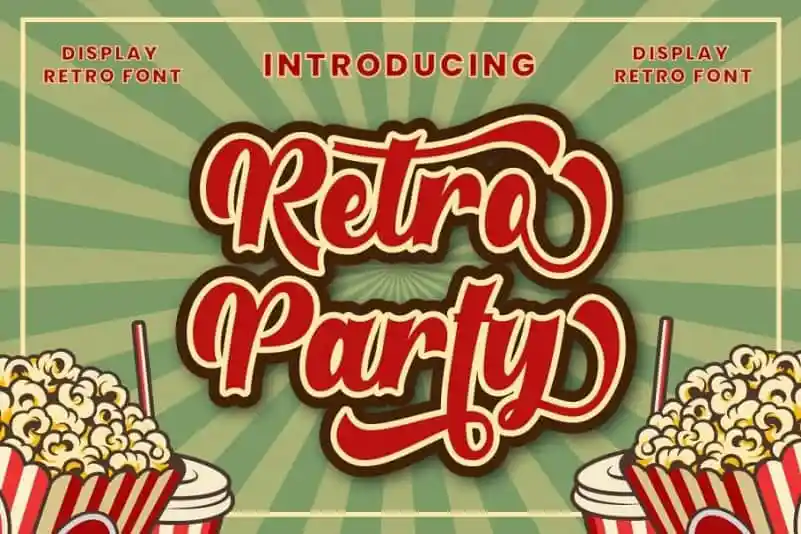
Retro Party Script Font – Download Grátis
Introduzimos a Retro Party Script Font, uma tipografia script sem ser muito formal. Cria-se desta mão-de-vaca do designer PutraCetol Studio. Inspirada por alguns tipos retro que fizemos antes. Retro Party é perfeito para design vintage e retro como logotipos, camisetas, posters, marcação, embalagem, sinalização, capa de livro e muito mais! Esperamos que você goste dela.